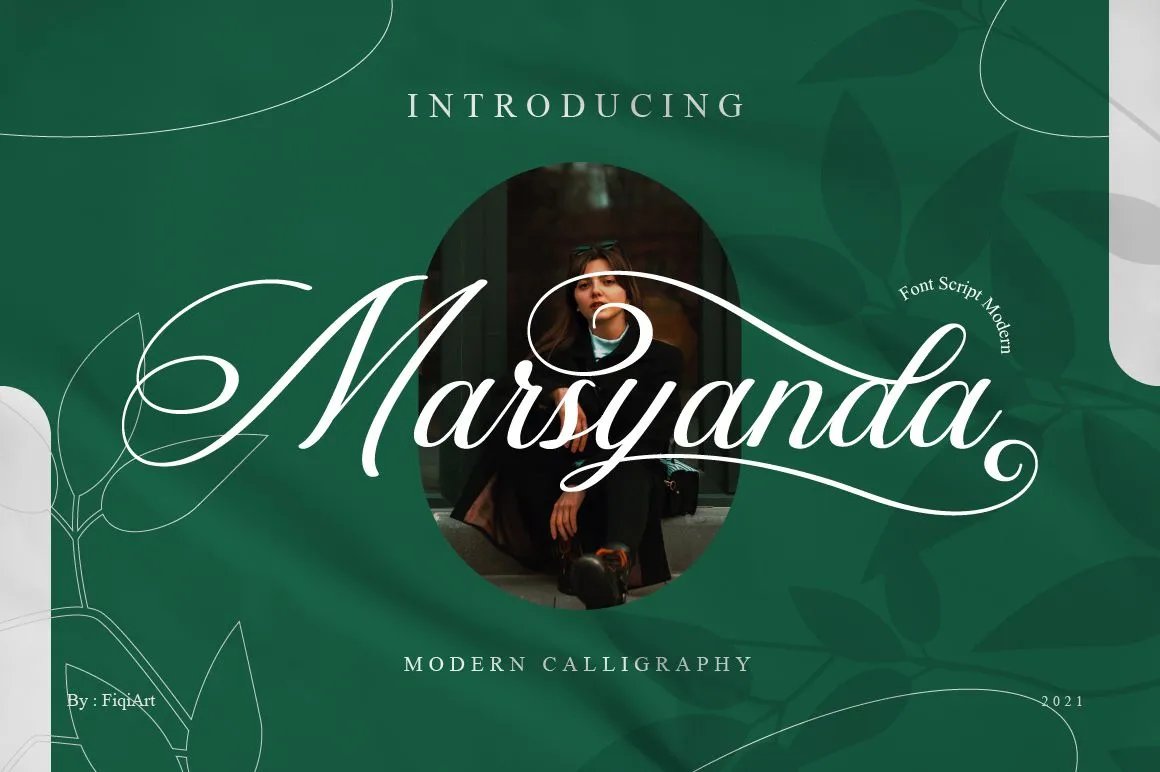
Marsyanda Font – Download Grátis
A Marsyanda Font é uma elegante tipografia à mão escrita que transmite romantismo e suavidade. Suas letras dançam sobre a linha de base, criando um efeito sofisticado e encantador. Esta fonte incorpora símbolos PUA que permitem acessar facilmente todos os caracteres únicos e ligaturas, tornando-a perfeita para qualquer projeto gráfico. Seja ela uma criação para cartões personalizados ou design de editoriais de jornal, a Marsyanda Font enriquecerá seu trabalho com um toque de luxo e charme. Não espere mais – transforme seus projetos em obras de arte com essa fonte única e sofisticada.